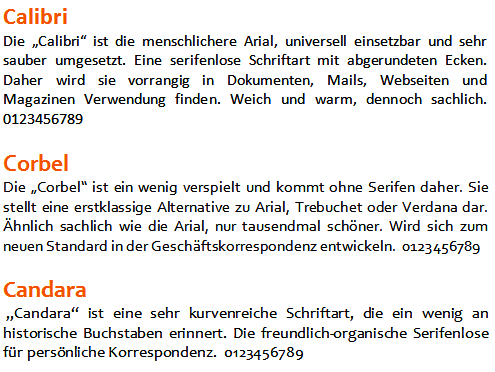
Welche Sans für Informationsbroschüren eines Krankenhauses
nachdem ich mich jetzt einige Zeit mit Schriften befasst habe (viel zu kurz) stellt sich mir jetzt mein erstes Schriftenproblem, an dem ich dann aber auch gleich verzweifle.
Gesetzt werden soll eine Informationsbroschüre eines Krankenhauses, d.h. es werden hohe Anforderungen an die Lesbarkeit gestellt.
Folgende Rahmenbedingungen: DIN A4, einseitig bedruckt, linker Rand geklebt (Wie bei Dr. Arbeiten)
bisher darin verwendet: 12 pt Arial, nicht ganz einheitlicher Zeilenabstand zwischen 1,5 und 2 fach. Natürlich mit grauseligem Blocksatz ohne Silbentrennung.
Welche Sans Schriften könnt ihr denn für eine gute Lesbarkeit empfehlen und welchen Zeilenabstand vertragen sie noch um eine gute Zeilenführung zu erhalten. Mit den riesen Zeilenabständen finde ich es nämlich wahnsinnig schwer ansprechend zu Layouten.
Wie man wahrscheinlich aus den Rahmenbedingungen ersehen kann, darf dass ganze natürlich nichts kosten. Darum macht das ja auch ein Medizinstudent und keine Agentur :?
darf nix kosten? Also Systemschriften.
Franklin Gothic käme in Frage. Oder Univers. Die Franklin kommt auch mit nem großen Zeilenabstand zurecht.
Mit 1,5fachem Zeilenabstand kommt die ganz gut klar. Mir ist gerade der Jahresbericht von »The Leverhulme Trust« in die Hände geraten, gesetzt in der Scala, und ich fand das recht ansprechend, muß ich sagen.
Wie sieht das mit der Myriad Pro aus? Die kommt mit dem Acrobat Reader (EULA lesen; ich habe schon wieder vergessen, wie das mit den Rechten ist!). Meines Erachtens wäre sie für sowas etwas zu glatt, andererseits wieder robust genug, um einen etwas weiteren Zeilenabstand ertragen zu können.
Oder die beiden serifenlosen Office2007-Schriften? Calibri und Corbel, beide m.E. für Fließtext besser geeignet als eine 12 pt Arial. Liegen dem kostenlosen PowerPoint Viewer bei.
Es sind drei seriflose. Calibri, Corbel und Candara. An die habe ich auch gedacht.
Ja, die Candara verdränge ich immer, die ist mir persönlich zu »Öko«. Ich weiß, ich weiß, das kommt drauf an wie sie eingesetzt wird, ist aber trotzdem so ein permanentes unterschwelliges Bauchgefühl bei mir. :roll:
Ja, wie die Verdana (*und Tahoma?), obwohl sie meine WinVista Lieblingssans ist, schade.
Meine Erfahrungen mit den genannten drei Vista-Schriften:
* Candara sieht in üblichen Lesegraden irgendwie fleckig aus, da kommen die ungleichmäßigen Strichstärken noch nicht gut zur Geltung, hinterlassen bei mir nur den Eindruck "unsauber".
* Calibri kann man sehr gut in 12pt, 1,4-facher Zeilenabstand einsetzen - ist zwar viel kleiner als Arial 12pt, aber gerade deswegen passt sie in 12pt ja besser ... :cheer: In größeren Schriftgraden, Headlines etc stören mich aber die verrundeten Zeichenformen - sieht in meinen Augen dann unscharf aus, ob das jetzt gerade hip ist oder nicht.
* Persönlich ist mir die Corbel noch lieber: frischer, etwas lebendiger als die Calibri und gut in Schriftgraden von 9pt - 16pt einsetzbar. Bedenk aber: Deren normale Ziffern sind Medieval-Ziffern! Und, korrekt: Die Abführer" hängen grässlich nach rechts weg :peng:
keine bedenken! in allen vista-cleartype-fonts stehen mediäval- und versalziffern zur verfügung, sowohl mit variabler als auch mit fester dickte für den tabellensatz. in der calibri, der constantia und der corbel gibt es sogar kapitälchenziffern auf x-höhe. wie schon oft gesagt: die fonts von microsoft sind besser als ihre software, denn in word zum beispiel kann man tatsächlich nur jeweils eine der ziffernarten komfortabel nutzen. aber die broschüre wird wohl in einem opentype-fähigen programm layoutet. ich würde mich übrigens auch zwischen der corbel und der calibri entscheiden, mit leichter tendenz zur letzteren. die corbel hat nämlich ein etwas komisches ›u‹, außerdem mag ich die rundungen der calibri.
... die corbel hat nämlich ein etwas komisches ›u‹, außerdem mag ich die rundungen der calibri.
oooh, dieses allerliebste "u" :biglove: ist doch gerade das Sahnehäubchen auf der Corbel ...
Gerade wenn du die Schriften neben ähem untereinander stellst, sieht man doch den übergroßen ästhetischen Vorsprung der Corbel, schöne Schrift! :huhu:
dann stellen wir doch mal gleich alle neben- bzw. untereinander, außer der consolas, die als monospace-schrift ja etwas eingeschränkt in der nutzung ist:
wie ist euer ranking und warum? ich schreibe später auch was dazu.
Mein Ranking: Calibri und Corbel obenauf, dann der Rest. Übrigens ist die Consolas auch nicht zu verachten. Ich benützt sie im Code-Editor. Sie ist für mich angenehmer und eindeutiger/klarer als die Courier New.
Wobei ich ja sagen muß, daß ich diese »Waldorf-Schriften« ja ziemlich ausnahmslos häßlich finde wie die Nacht!
Aber z. B. FF Liant hat doch was, oder?
ich mag diese anthroposophische schriften im stile von ff liant ja.
vorallem wenn sie passend eingesetzt sind, wie bei weleda.
Die Corbel kommt bei uns ja wegen der falsch gezeichneten Anführungszeichen gar nicht nicht in Frage. (Dieses Schicksal teilt sie mit der Comic Sans.)
Ist dass Problem nicht längst in den aktuellen Versionen behoben?